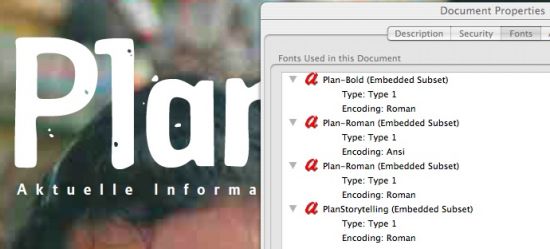
Um welche Schrift handelt es sich!
wenn du was ähnliches suchst - zumindest das a sieht aus wie ketchupa von fountain.
Was 'n das für'n Sch.. Name für 'ne Schrift?
wir hatten doch neulich die «Svenska Sauerkrauta bold» oder so ähnlich …
"One day at lunch, having a hamburger, I looked at the ketchup package and noticed how the ink in the print had spread and made the small size lettering look very round. Using Corpus Gothic as a template, I've tried to imitate this in Ketchupa and Mustardo. "
eine sauerkrauto gibts übrigens auch von peter bruhn.